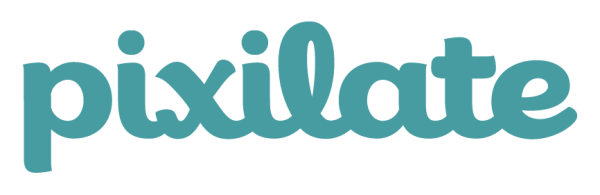
• Land: Schweden
• Ort: Helsingborg
Pixilate ist ein schwedisches Schriftenlabel, das von Kemie Guaida betrieben wird. Das Label hat sich auf Handschriften spezialisiert.